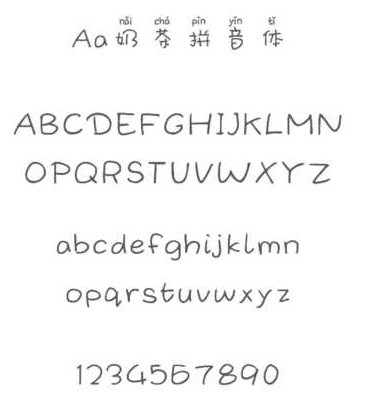
奶茶拼音ttf是字體管家推出的一款拼音字體,中文漢字充滿童真活潑之氣,英文圓潤(rùn)可愛,在漢字的上方有著對(duì)應(yīng)的拼音和聲調(diào),不僅讓文字更易發(fā)音,也有不錯(cuò)的藝術(shù)效果,喜歡的朋友就來綠色資源網(wǎng)試試吧!
奶茶拼音體是用漢語(yǔ)拼音制作的字體,適合出版印刷和小學(xué)語(yǔ)文教學(xué)使用,按數(shù)字鍵就會(huì)出現(xiàn)字母帶音標(biāo),是一款非常實(shí)用的卡通字體。
奶茶拼音字體可以讓每一個(gè)漢字都帶有拼音,字體庫(kù)全面好用,可以通過手機(jī)學(xué)習(xí)漢字拼音哦,字體庫(kù)非常齊全,不會(huì)出現(xiàn)亂碼顯示等問題,適合用于書籍、報(bào)刊、雜志的標(biāo)題和宣傳裝飾用字。